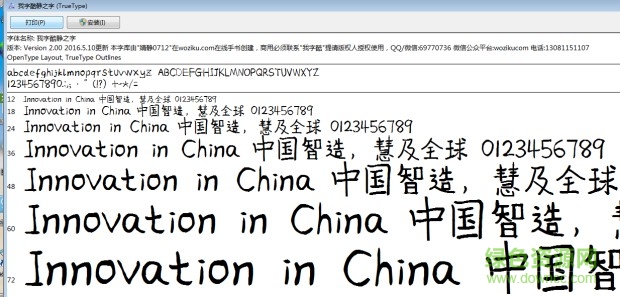
軟件介紹 軟件標(biāo)簽: 我字酷 字體 我字酷靜之字體是一款非常好看的字體,這款字體字形可愛又大方,不管是廣告用語還是設(shè)計(jì)專用都非常適合哦,有喜歡的朋友就來綠色資源網(wǎng)下載吧!我字酷靜之字體介紹我字酷靜之字體是一款用于手寫設(shè)計(jì)方面的字體,由綠色資源網(wǎng)提供免費(fèi)下載。靜之字體預(yù)覽字體安裝方式方法一:控制面板/字體/文件/安裝新字體;方法二:直接將字體復(fù)制到C:\WINDOWS\Fonts。方法三:針對win7系統(tǒng),用戶只需選中字體右鍵安裝即可。 軟件截圖 上一張下一張(1 / 1) 安裝詳細(xì)截圖 其他版本下載 標(biāo)題 大小 更新日期 下載 我字酷無非 1.32M 2017-02-25 下載 我字酷默陌寫意水墨體字體 免費(fèi)版 2.39M 2017-06-14 下載 我字酷默陌枝椏字體 2.45M 2017-08-17 下載 下載地址 電腦版 靜之字體 點(diǎn)擊報(bào)錯 軟件無法下載或下載后無法使用,請點(diǎn)擊報(bào)錯,謝謝! 關(guān)閉報(bào)錯反饋 請描述您所遇到的錯誤,我們將盡快予以修正,謝謝! *必填項(xiàng),請輸入內(nèi)容 本類最新 dreamweaver字體庫 首爾南山體字體 v1.06 官方版 潮字社風(fēng)云簡ttf 潮字社凌渡鯤鵬簡體字體 潮字社曾玉波手書簡字體 微博慧心字體 相關(guān)文章 Photoshop字體安裝使用方法和技巧 如何解決“無法新增字體”問題 Win 7系統(tǒng)安裝字體方法 網(wǎng)頁字體大小設(shè)置方法 怎么改網(wǎng)頁字體大小 在Linux系統(tǒng)中安裝字體的幾種方法 windows7字體顯示問題:打開某些程序的時(shí)候顯示的是亂碼 用戶評論 熱門評論 最新評論 發(fā)表評論 查看所有評論(0) 昵稱: 請不要評論無意義或臟話,我們所有評論會有人工審核. 字?jǐn)?shù): 0/500 (您的評論需要經(jīng)過審核才能顯示)